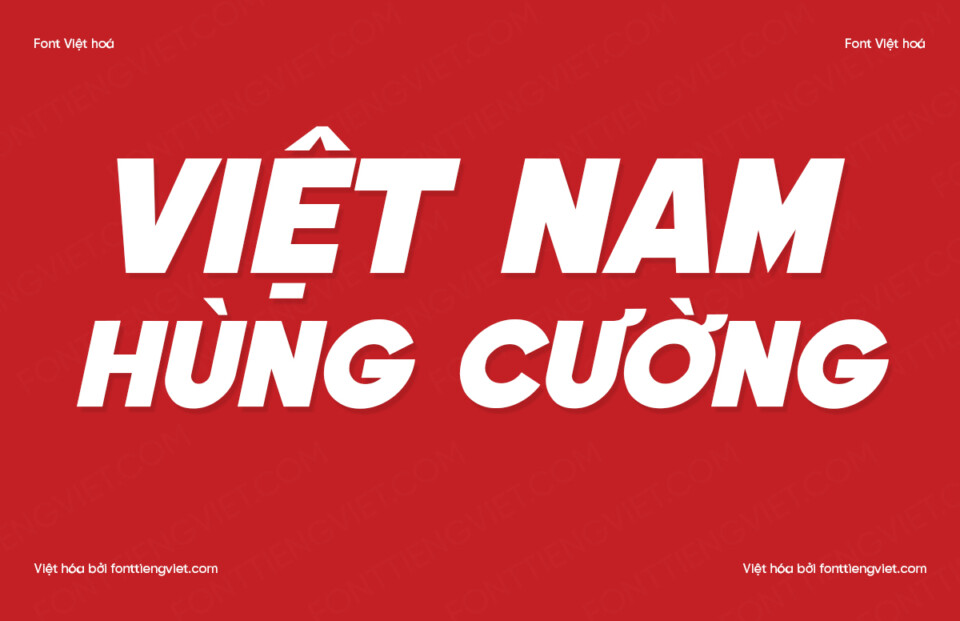
Font Việt hóa 1FTV VIP Edges Italic
Giới thiệu về bộ Font Việt hóa 1FTV VIP Edges Italic
Trong thế giới thiết kế đồ họa ngày nay, việc lựa chọn một bộ Font Miễn Phí chất lượng đóng vai trò then chốt giúp sản phẩm của bạn trở nên nổi bật và chuyên nghiệp hơn. Đặc biệt, đối với các bạn học sinh và sinh viên đang làm quen với công cụ thiết kế, Font Việt hóa 1FTV VIP Edges Italic nổi lên như một lựa chọn hàng đầu nhờ phong cách tối giản nhưng vô cùng tinh tế. Đây là phiên bản nghiêng đầy cá tính, mang lại cảm giác chuyển động mạnh mẽ và hiện đại cho mọi khung hình. Bộ font này không chỉ hỗ trợ đầy đủ bảng mã tiếng Việt mà còn được tinh chỉnh kỹ lưỡng về khoảng cách, giúp các đoạn văn bản trở nên dễ đọc và bắt mắt hơn bao giờ hết.
Tại sao bạn nên chọn Font Việt hóa 1FTV VIP Edges Italic?
Lý do khiến Font Việt hóa 1FTV VIP Edges Italic được cộng đồng Designer Việt Nam ưa chuộng chính là sự cân bằng giữa nghệ thuật và tính ứng dụng. Các đường nét sắc sảo (Edges) kết hợp cùng độ nghiêng (Italic) tạo nên một diện mạo trẻ trung, năng động. Font chữ này rất phù hợp để làm tiêu đề cho các slide thuyết trình bài giảng, thiết kế bìa báo tường, hoặc tạo các trích dẫn ý nghĩa trên mạng xã hội. Khi sử dụng font này, bạn sẽ nhận thấy sự chỉn chu trong từng nét chữ, từ dấu huyền, dấu sắc cho đến các ký tự đặc biệt, đảm bảo không xảy ra lỗi hiển thị khi gõ tiếng Việt trên các phần mềm như Photoshop, Canva hay Word.
Ứng dụng thực tế của Font Việt hóa 1FTV VIP Edges Italic trong học tập
Đối với môi trường giáo dục, việc trình bày văn bản một cách sáng tạo sẽ giúp tăng cường khả năng tiếp thu kiến thức. Font Việt hóa 1FTV VIP Edges Italic thường được các thầy cô giáo sử dụng để tạo điểm nhấn cho các tiêu đề chương học hoặc các ghi chú quan trọng trong giáo án điện tử. Các bạn học sinh cũng có thể dùng nó để trang trí thiệp chúc mừng, thiết kế logo cho lớp hoặc làm đẹp cho các dự án cá nhân. Sự linh hoạt của font chữ này cho phép nó thích nghi tốt với cả phông nền sáng và tối, giúp thông điệp truyền tải luôn rõ ràng và ấn tượng nhất.
Hướng dẫn sử dụng font hiệu quả
Để phát huy tối đa vẻ đẹp của Font Việt hóa 1FTV VIP Edges Italic, bạn nên kết hợp nó với một font chữ không chân (sans-serif) dạng đứng cho phần nội dung chính. Việc tạo ra sự tương phản giữa chữ nghiêng của tiêu đề và chữ đứng của văn bản sẽ giúp bố cục trang giấy có chiều sâu hơn. Ngoài ra, hãy chú ý đến việc lựa chọn màu sắc; những tông màu pastel hoặc màu tương phản mạnh sẽ làm tôn lên các đường cạnh sắc nét của bộ font này, mang lại hiệu ứng thị giác tuyệt vời cho người xem ngay từ cái nhìn đầu tiên.
Việc nâng cao chất lượng thẩm mỹ cho mỗi bài thuyết trình hay tài liệu học tập chưa bao giờ dễ dàng hơn thế với sự trợ giúp của Font Miễn Phí, Font Việt Hóa, Font Việt hóa 1FTV VIP Edges Italic. Hãy làm quen với việc kết hợp các font chữ Việt hóa chất lượng cao để rèn luyện tư duy thiết kế từ sớm. Bằng cách sở hữu Font Việt hóa 1FTV VIP Edges Italic, bạn không chỉ có thêm một công cụ hỗ trợ tiếng Việt hoàn hảo mà còn khẳng định được phong cách cá nhân đầy sáng tạo và mới mẻ. Chúc các bạn học sinh và quý thầy cô sẽ tạo ra nhiều tác phẩm đồ họa thật ấn tượng và mang đậm dấu ấn riêng qua bộ font chữ độc đáo này.